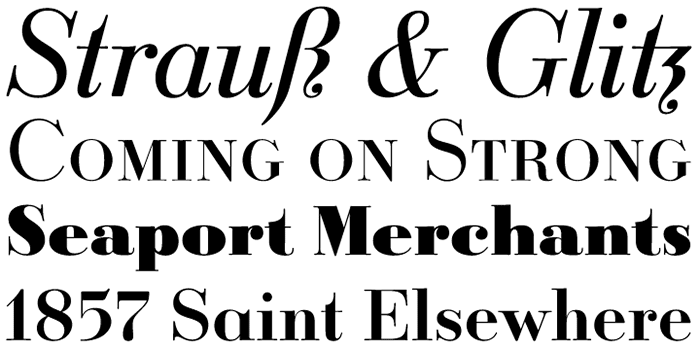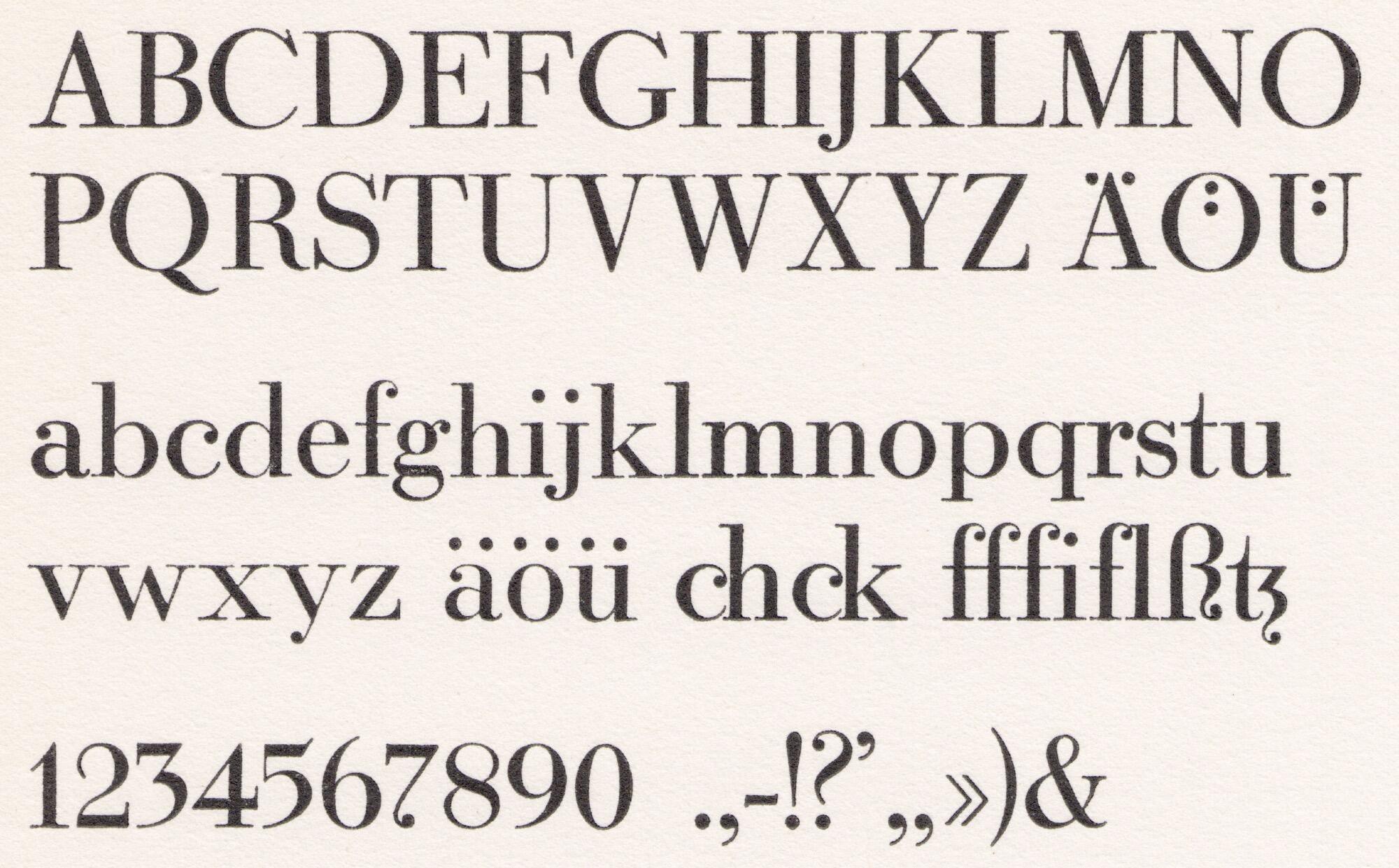
- 1923
- Antiqua statisch
Die Ratio-Latein von F.W. Kleukens erschien ab 1923 bei der D. Stempel AG. Auf den ersten Blick ist sie eine typische klassizistische Antiqua mit ausgeprägten Tropfenserifen, doch in den Details zeigen sich einige Besonderheiten wie die spitzen Sporne am Stammende des t oder die eigenwillige Form des Eszett, die sich auch in der Kleukens-Antiqua findet.
Die ursprüngliche Bleisatz-Version verfügte über die Schnitte normal, kursiv, halbfett und fett. Außerdem gab es zusätzlich lichte Ratio-Versalien, so genannte freie Versalien und blumenverzierte Initialen.
Die Grundschnitte sind seit 2011 in einer Digitalisierung mit dem Namen Ratio Modern über Canada Type erhältlich.